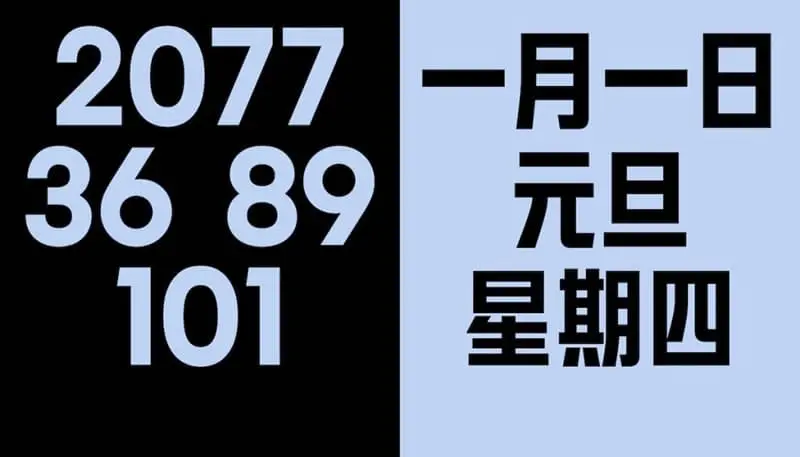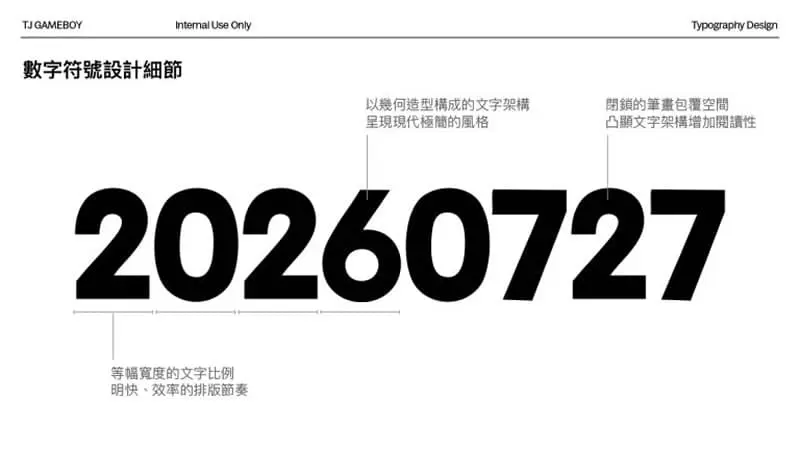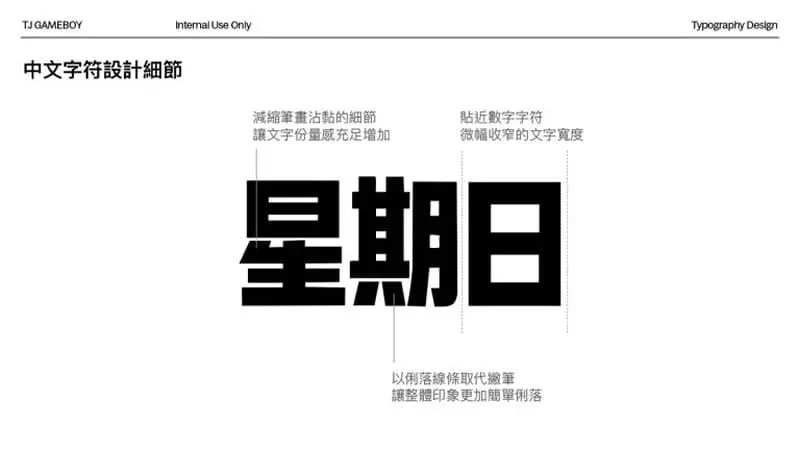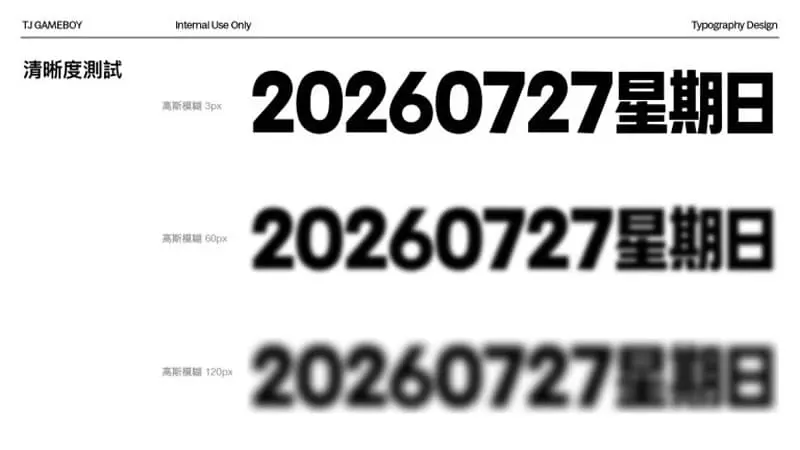
你有想過,從小翻到大的日曆,其實沒有自己專屬的字體嗎?
台中的「存在日曆」是一間經營五十年的資深日曆廠,半個世紀以來每天印製日曆,見證著台灣人的生活一頁頁翻過。然而在製作日曆的過程中,他們發現了一個有趣的現象,台灣的日曆,竟然沒有屬於自己的字體。
傳統日曆大多使用粗黑體或襯線體,這是因為早期華人社會習慣將日曆掛在客廳、餐桌等公共區域,任何人走過都要能輕鬆看到日期,因此「遠距離清楚辨識」是最重要的考量。
但隨著時代演進,這些傳統字體逐漸出現問題:
- 數字、月份、星期經常使用不同字體,近看顯得瑣碎雜亂
- 中文字為了排版常被暴力變形,有時被壓扁、有時被拉長
- 粗黑體雖然遠看清楚,近看卻缺乏美感
- 幾十年來從未統一,也沒有正式名稱
過去大家覺得「日曆反正都要撕掉」,所以不太在意這些細節。但存在日曆認為,既然要創造日曆的新用法,就應該連字體一起革新!
從共編曆到日曆體:一場文化革新運動
2021年,存在日曆發起了「共編曆計畫」,製作台灣第一本由全民共創的日曆,這本日曆由 365 位網友投稿而成。既然有「共編」,當然更要「共享」,於是他們決定開發台灣第一套專屬日曆字體「日曆體」。
存在日曆與字體設計師泰江(TJGameboy)攜手合作,以 50 年的日曆製造經驗為基礎,共同打造出這套兼具傳統辨識性與現代美感的全新字體。
設計理念:遠近都清晰
為了因應現代小家庭、小空間的生活型態,「日曆體」最重要的任務就是讓遠近距離都能看清。傳統粗黑體雜亂,現代細字體近看舒服卻遠看模糊,設計團隊的挑戰就是讓這兩個極端能同時並存。
日曆體的三大設計特色
1. 幾何無襯線的數字設計
數字部分採用幾何無襯線(Geometric Sans Serif)風格,以純粹的直線與圓形構成筆畫。粗度沉穩卻不笨重,無論遠距或近距都能清晰辨識。設計團隊特別在筆畫閉口處調整比例,讓數字結構更穩定,閱讀性更高。
2. 簡潔俐落的中文字形
中文字設計採用簡潔風格,曲線拉直、字面略收窄,呼應數字比例並增添精神感。收窄的文字寬度讓排版更穩定,也貼近傳統日曆方正的格局。減少筆畫重疊的細節,使整體更乾淨、有份量。
3. 協調一致的視覺節奏
整體設計的關鍵,是讓數字與中文在同一頁面上能夠協調共存。設計團隊重新調整灰度、字重與字距,確保「日期」、「星期」、「月份」並排時能維持一致的視覺節奏,讓整體版面既清楚又有呼吸感。
結語:屬於所有人的日曆字體
比起單純的字體設計,「日曆體」的誕生更像是一場文化革新。它源自日曆廠的現場經驗與對時代的觀察,希望讓「日曆」作為台灣人生活的一部分,也作為時間的共同語言,能因應時代需求而改變,讓「日曆」重新被看見。